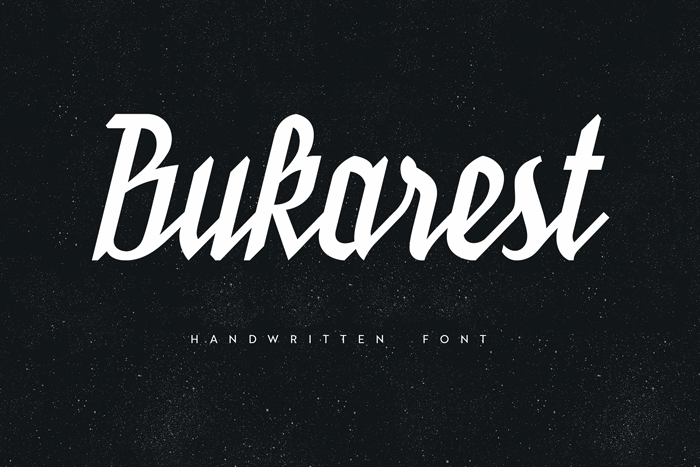
Bukarest Handwriting Font – Download Grátis
A fonte Bukarest Handwriting é perfeita para quem busca uma letra cuidadosa com estilo moderno. Desenvolvida por Vinzent Britz, ela traz a elegância do desenho à escrita manuscrita. Esta fonte é ideal para diversos usos criativos, desde convites de casamento e logotipos até tags personalizadas e capas de produtos. Perfeita também para t-shirts customizadas ou blogs modernos, ela adiciona um toque sofisticado a qualquer projeto. Seja em sua versão digital ou impressa, a Bukarest Handwriting traz uma autêntica atmosfera de desenho à escrita que combina perfeitamente com estilos como graffiti e design web. Não importa qual seja o seu objetivo, esta fonte é um recurso vital para qualquer designer em busca de uma expressão única e sofisticada.